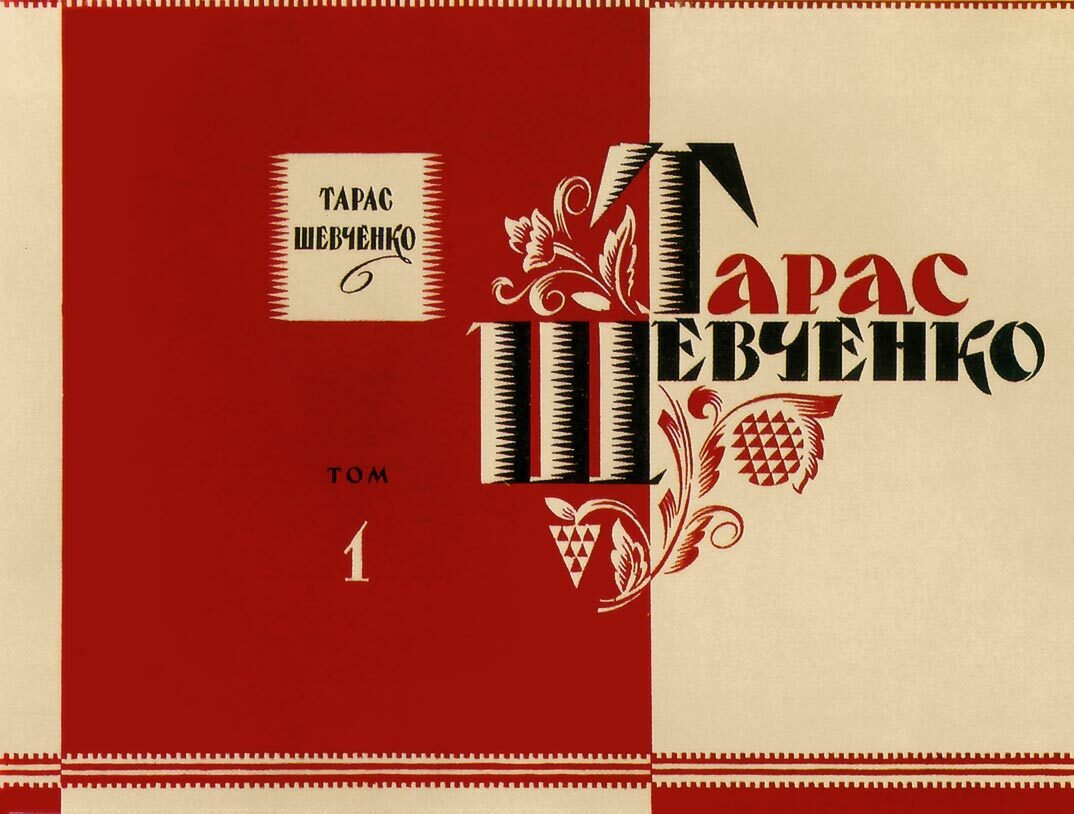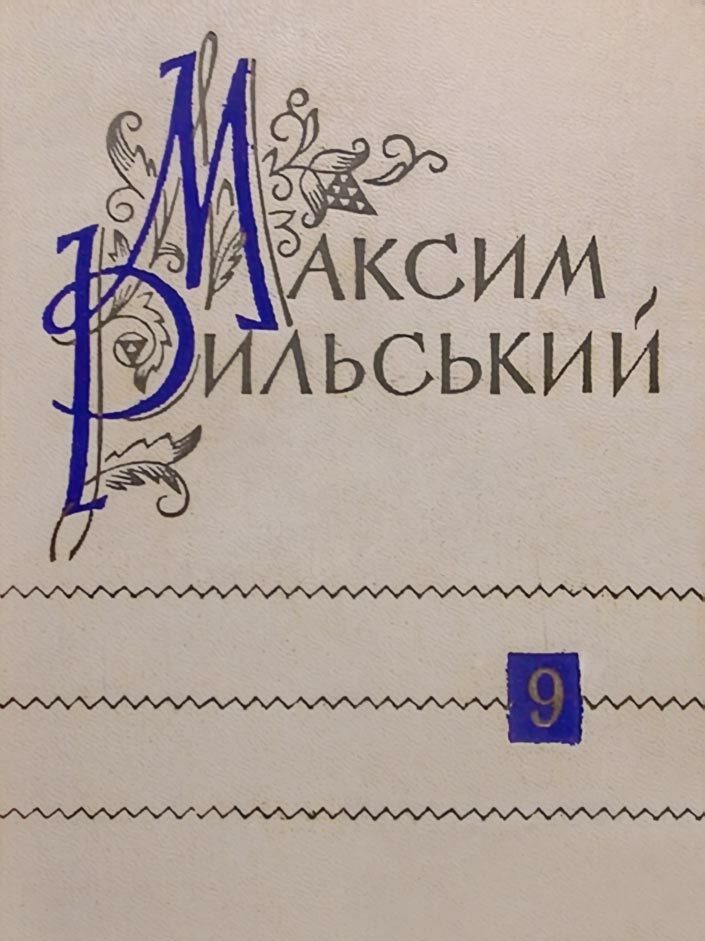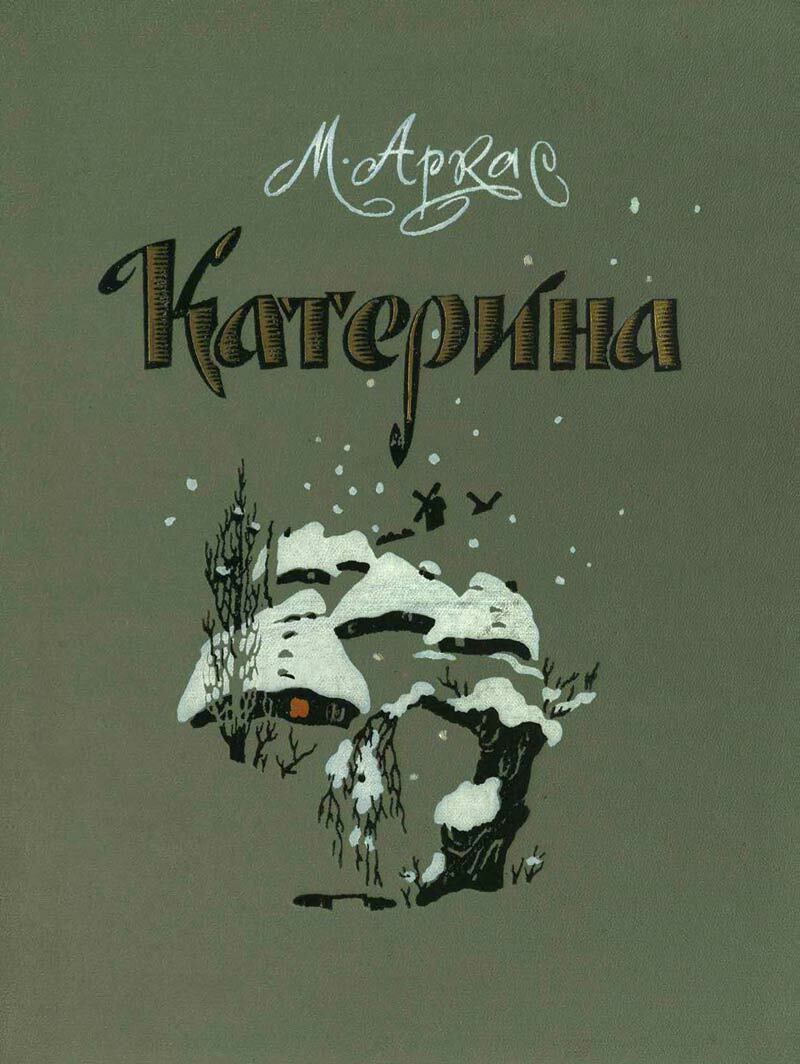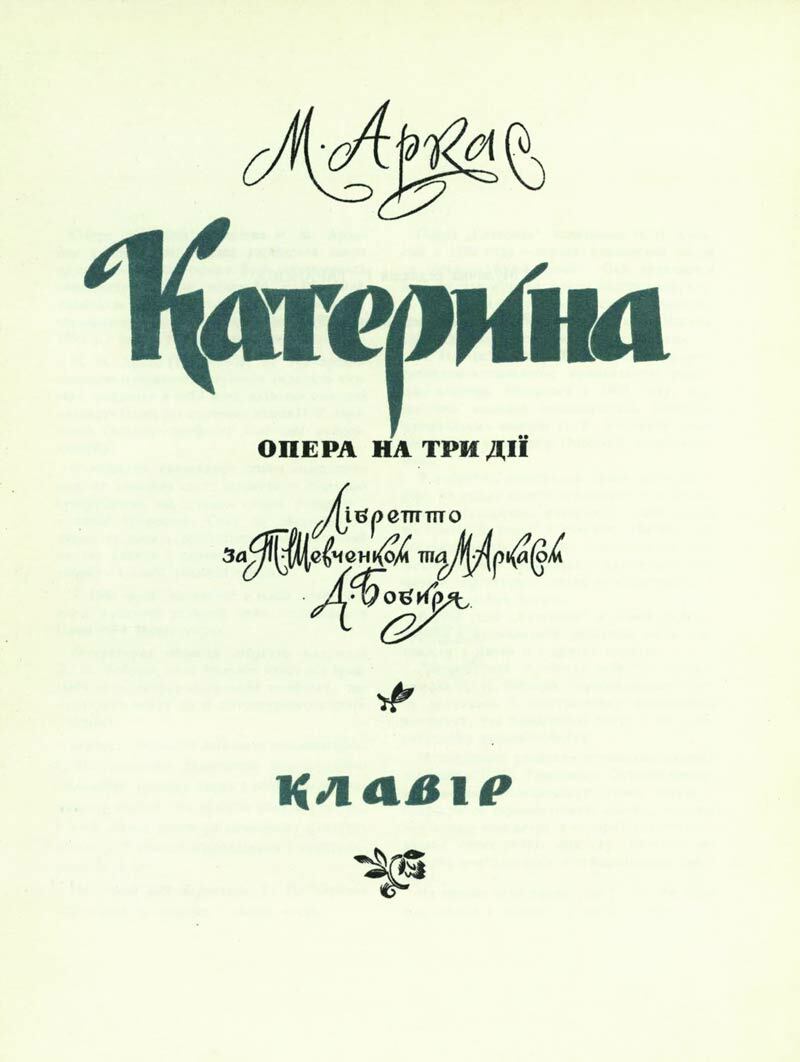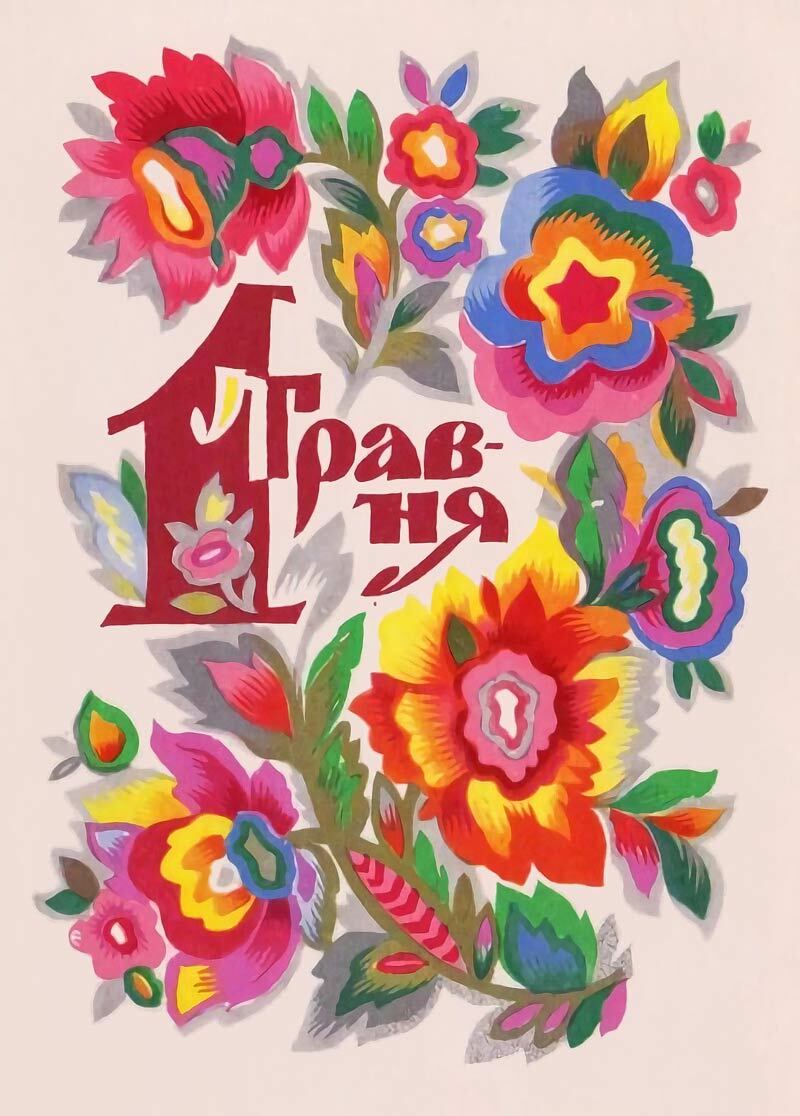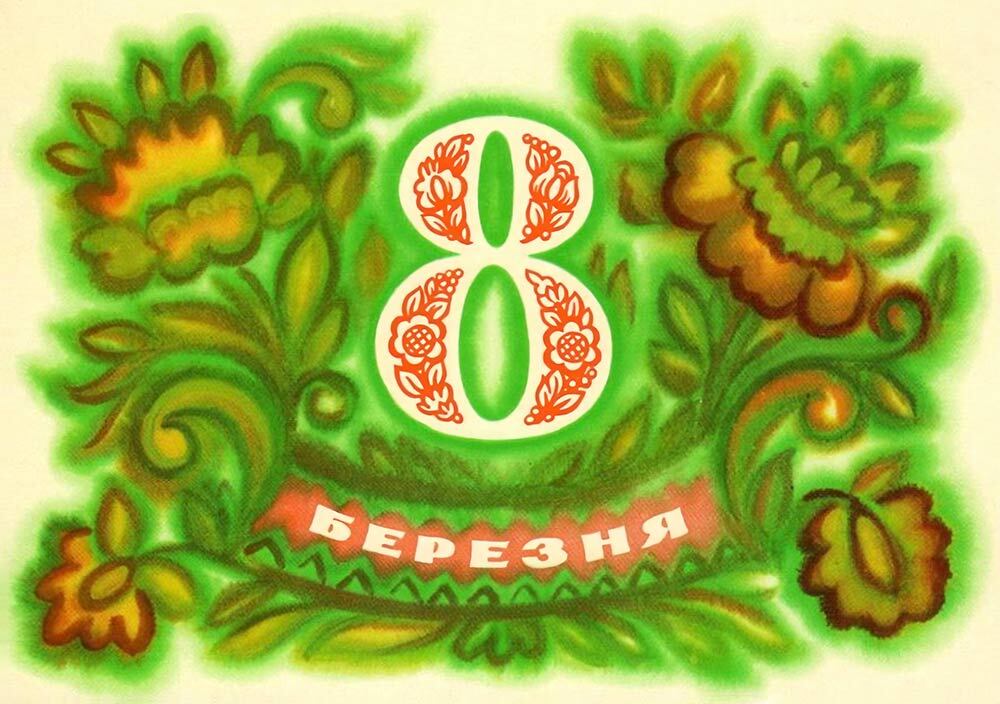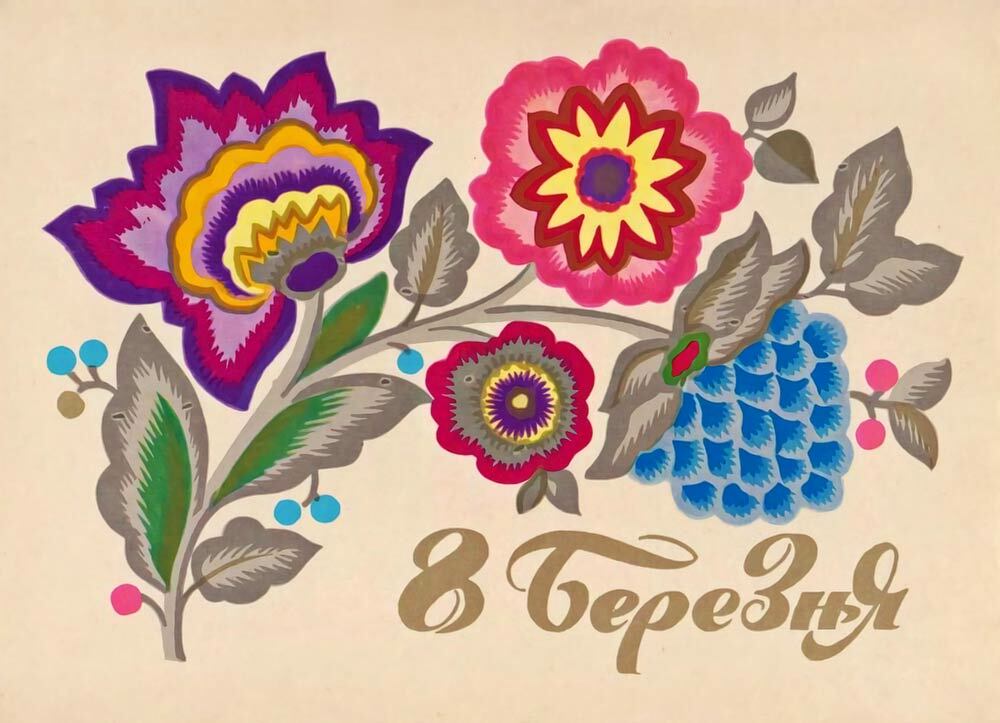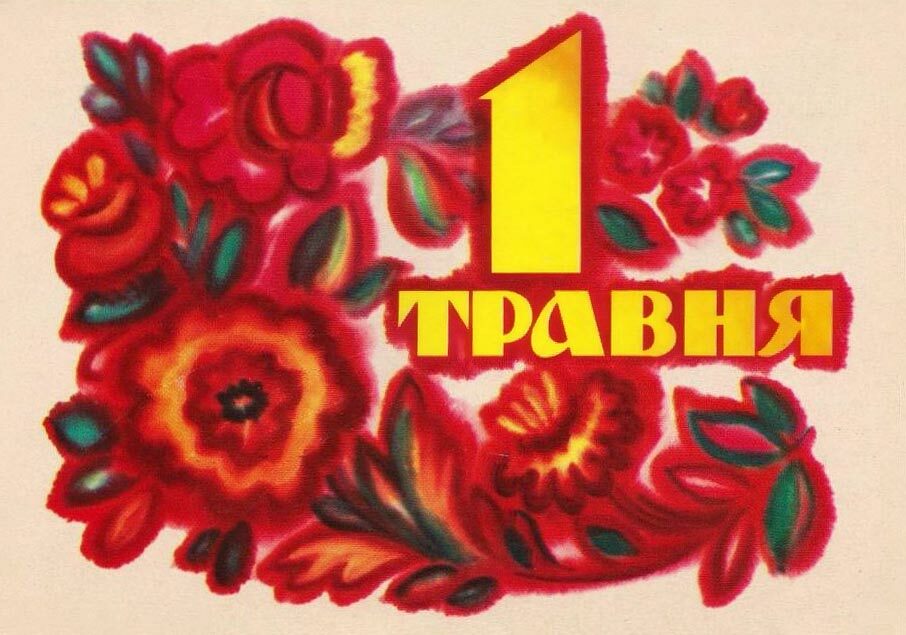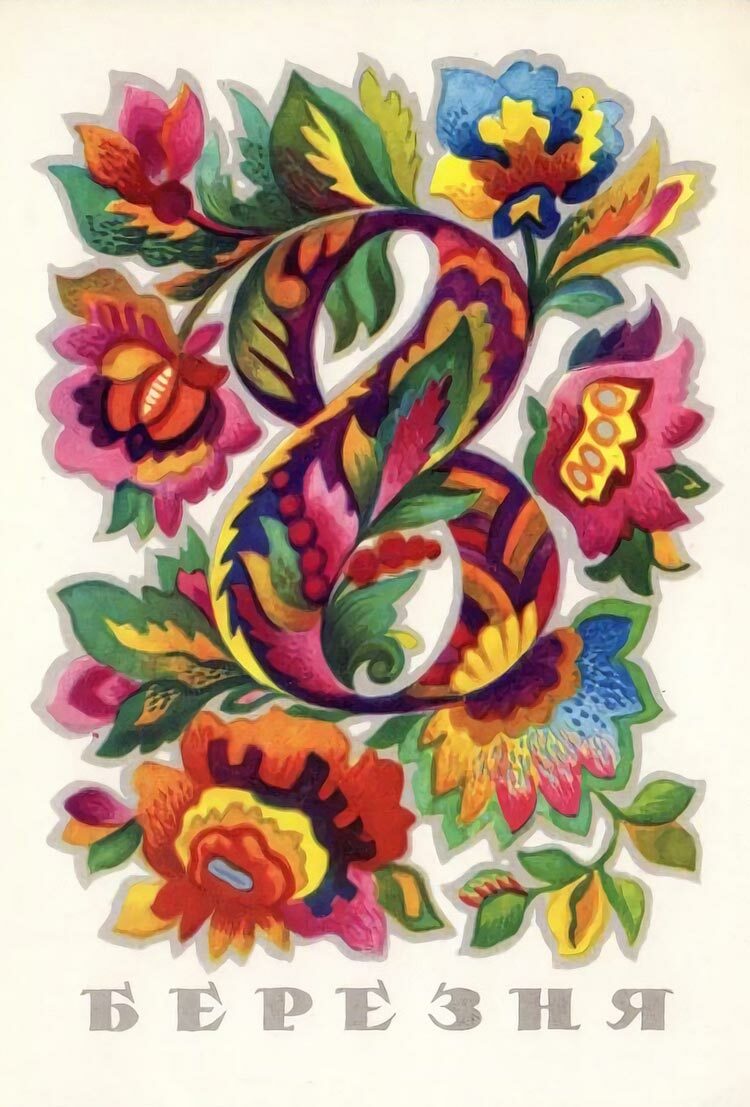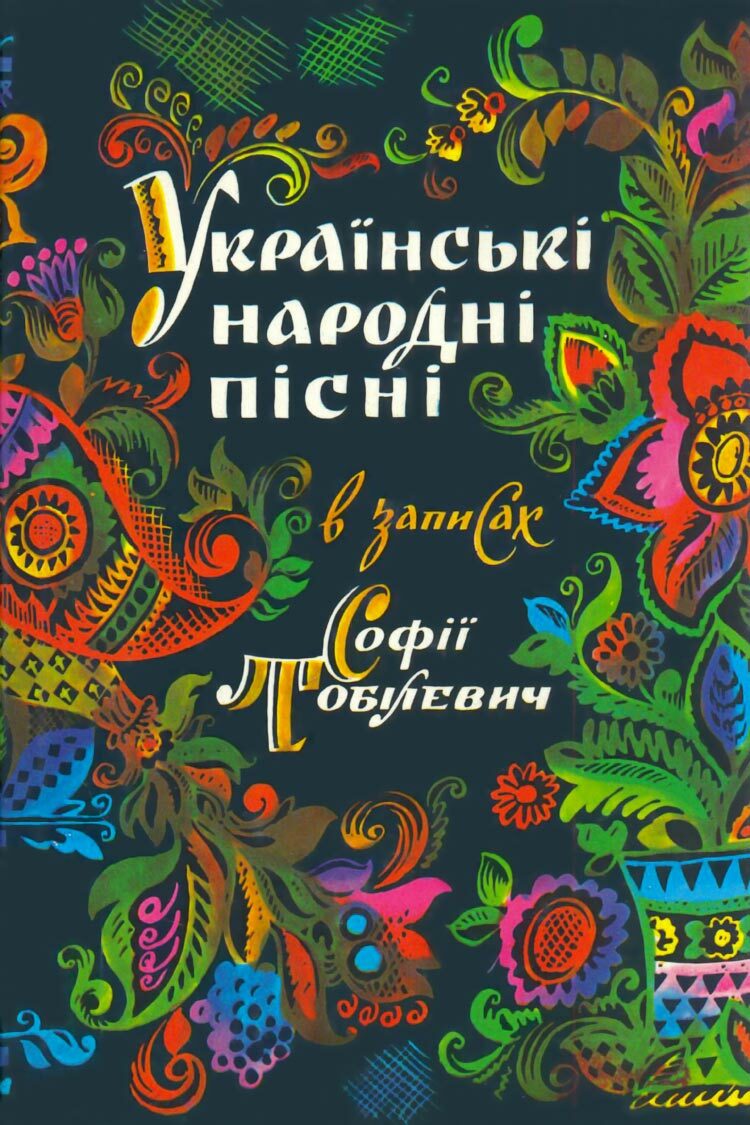
Анатолій Пономаренко (1922–2006)
Пономаренко Анатолий Федорович народився 12 листопада 1922 року у селі Катеринопіль Черкаської області. У 1946 році закінчив Київське художнє училище. З 1946 по 1952 працював на кіностудії ім. О. Довженка. Анатолій Пономаренко працював у сфері театрально-декораційного мистецтва та книжкової графіки, створював плакати і листівки. Помер у 2006 році.
1981 рік
Книжкова обкладинка. Літерація, декоративний розпис. Анатолій Пономаренко, 1981, Київ.
1974 рік
Святкова листівка до 8 Березня. Літерація, декоративний розпис. Анатолій Пономаренко, 1974, Київ.
Святкова листівка до 1 Травня. Літерація, акварель. Анатолій Пономаренко, 1974, Київ.
1973 рік
Святкова листівка до 8 Березня. Літерація, ілюстрація. Анатолій Пономаренко, 1973, Київ.
1972 рік
Святкова листівка до 8 Березня. Літерація, акварель. Анатолій Пономаренко, 1972, Київ.
Святкова листівка до 1 Травня. Літерація, декоративний розпис. Анатолій Пономаренко, 1972, Київ.
1963 рік
Книжкова обкладинка. Літерація, ілюстрація. Анатолій Пономаренко, 1963, Київ.
Титульний аркуш. Літерація. Анатолій Пономаренко, 1963, Київ.
1962 рік
Книжкова обкладинка. Літерація. Анатолій Пономаренко, 1962, Київ.
1961 рік
Книжкова обкладинка. Літерація, орнамент. Анатолій Пономаренко, 1961, Київ.